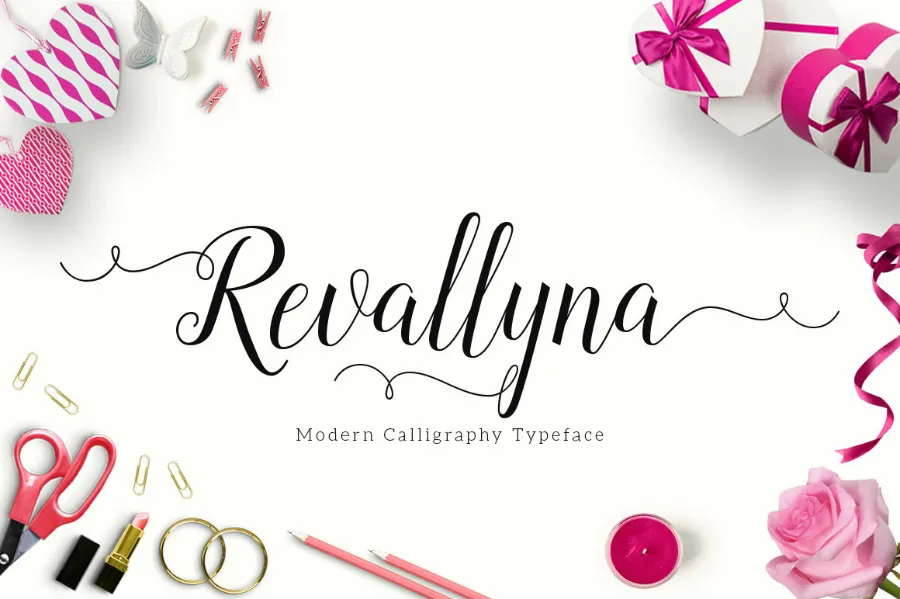
Revallyna Script Font – Fonte Grátis
Revallyna Script Font
A Revallyna Script é uma nova fonte de estilo tipográfico que traz alegria à sua composição visual, especialmente projetada para tornar seus designs mais profissionais e elegantes. Esta fonte de Hamilton foi criada e compartilhada com base em caracteres Unicode, fornecendo um toque moderno com um sabor nostálgico do estilo de escrita artística. Perfeita para aplicativos variados como convites, cartas de boas-vindas, materiais de marca, cartões de negócios, frases de autor e até mesmo as paredes com sua beleza decorativa que flutua harmonicamente ao longo da linha de base do texto. A Revallyna Script é uma opção perfeita para aqueles buscando um toque especial em seus projetos digitais ou impressos, dando um brilho único a qualquer tipo de material impresso.